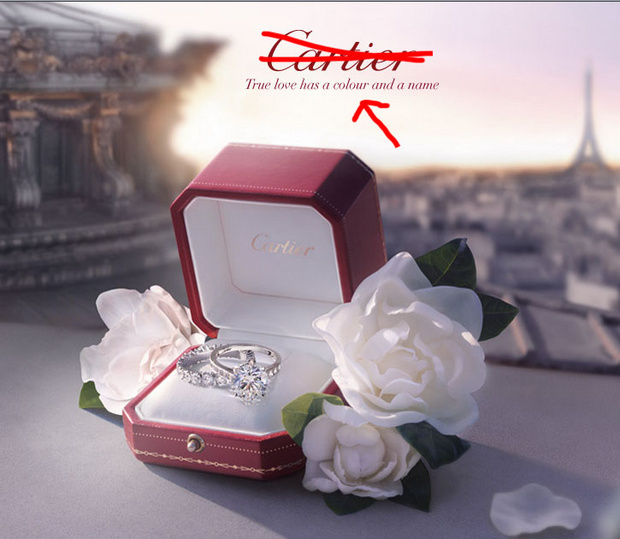
Wie heißt die Kursive bei Cartier ?
Es geht um die Kursive, die Cartier bei Anzeigen etc. verwendet. Nicht um den Cartier-Schriftzug.
Die Kursive hat ein sehr charakteristisches "v" und "w". Weiß jemand, wie diese Schrift heißt ?